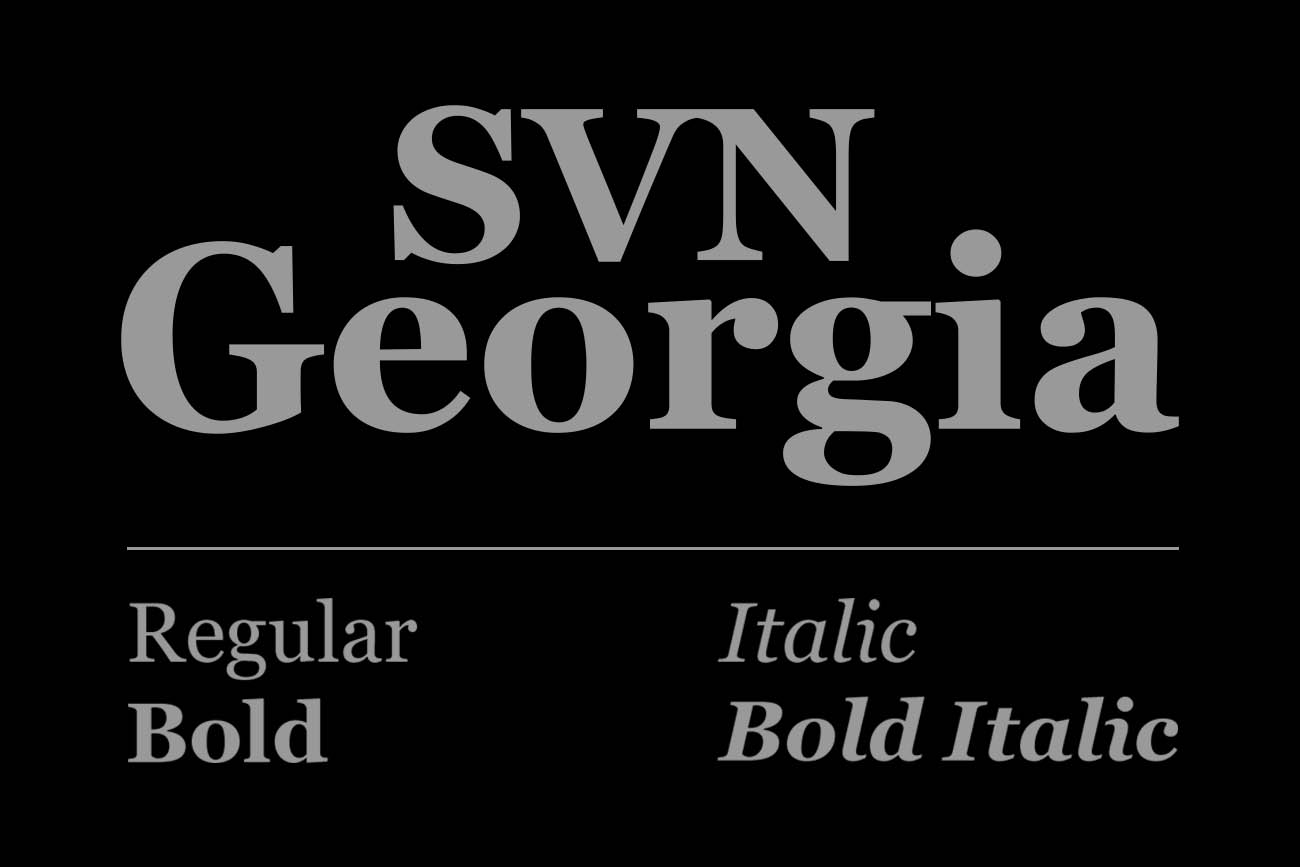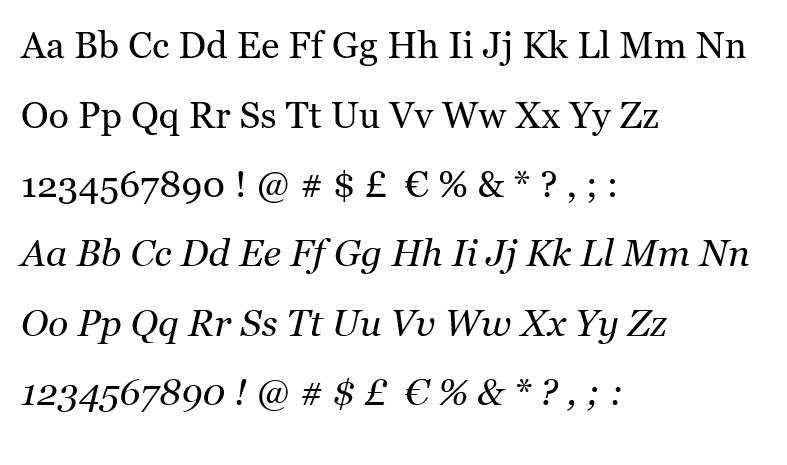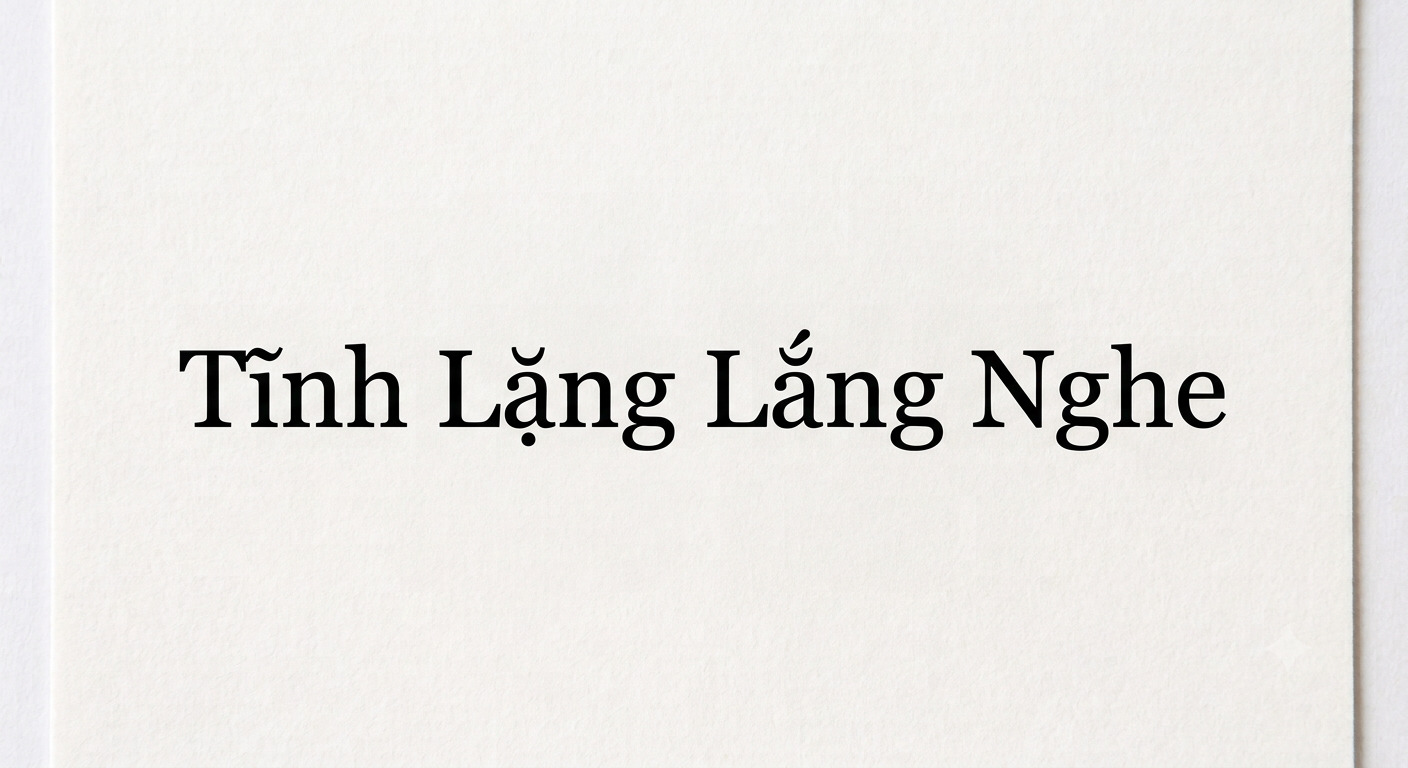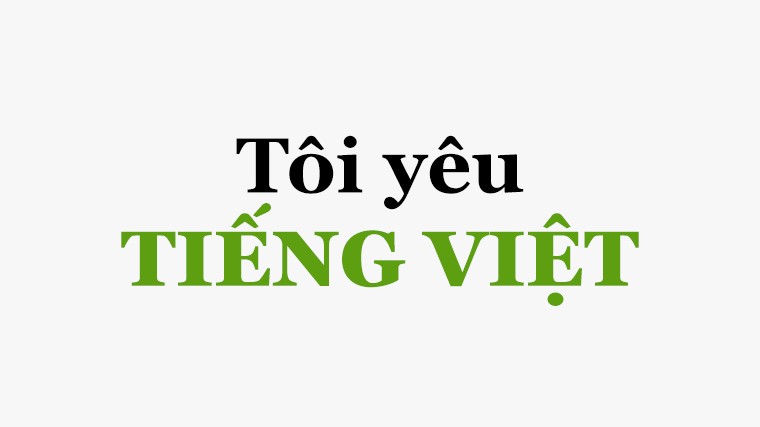
Georgia font Việt hóa là bộ phông chữ thuộc dòng Transitional Serif kinh điển được sáng tạo bởi bậc thầy Matthew Carter, thiết kế tối ưu hóa đặc thù cho việc hiển thị sắc nét trên màn hình máy tính có độ phân giải vừa phải và các tài liệu in ấn văn phòng. Với các đường chân chữ chắc chắn, bụng chữ rộng và chiều cao ký tự hào phóng, font Georgia Việt hóa là chất liệu trực quan tuyệt vời để các kiến trúc sư, kỹ sư trình bày các bản thuyết minh dự án nhà lắp ghép, hợp đồng kinh tế hay tài liệu báo cáo giám sát thi công.
Khung xương đầm ấm và độ sắc nét trên màn hình của Georgia font Việt hóa
Điểm cuốn hút của Georgia font Việt hóa nằm ở sự kết hợp giữa nét chữ truyền thống và kỹ thuật tối ưu hóa pixel hiển thị. Cấu trúc chân chữ có các đường cong chuyển tiếp dày dặn giúp con chữ bám chắc trên dòng kẻ ngang, ngăn ngừa hiện tượng lóa mắt khi đọc các văn bản dài.
Sự ổn định về mặt thị giác của dòng font này tạo nên cảm giác tin cậy, ấm áp và giàu tính tri thức. Khi kết hợp cùng các vật liệu kiến trúc cổ điển như tường gạch nung đỏ, vách gỗ sồi tự nhiên, biển đồng xước mờ hay rèm vải lanh trong các công trình nhà lắp ghép nghỉ dưỡng, Georgia tạo nên sự hòa quyện thẩm mỹ trầm mặc.
Tư vấn từ chuyên viên: Georgia được đánh giá cao về khả năng dàn trang văn bản dài (Body Text). Để bản thiết kế đạt hiệu quả thẩm mỹ tốt, bạn nên sử dụng phông chữ này cho phần nội dung mô tả chi tiết ở kích thước 10-12pt. Phần tiêu đề đề mục lớn có thể kết hợp cùng biến thể Bold hoặc một phông không chân hình học để tạo ra sự phân tầng thông tin rõ ràng và mạch lạc.
03 Ứng dụng font Georgia Việt hóa vào hồ sơ công trình
Nhờ vẻ ngoài mực thước và tính dễ đọc vượt trội, bộ phông chữ này mang lại giá trị thực tế lớn trong khâu hoàn thiện hồ sơ dự án xây dựng hiện đại:
- Thuyết minh giải pháp kiến trúc và Báo cáo hoàn công: Sử dụng font Georgia Việt hóa cho các văn bản giải trình kỹ thuật giúp tập hồ sơ trông ngăn nắp, thể hiện sự minh bạch và phong thái làm việc cẩn trọng của đơn vị thi công trước chủ đầu tư.
- Soạn thảo Hợp đồng kinh tế và Văn bản pháp lý: Những nét chân chữ vững vàng của Georgia rất ăn ý khi in ấn trên các biểu mẫu hợp đồng thi công nhà lắp ghép, tạo cảm giác đĩnh đạc và uy tín cho doanh nghiệp.
- Hệ thống biển chỉ dẫn và Bảng nội quy Homestay: Phông chữ này khi in trên các tấm gỗ sồi mộc hoặc bảng mica trong suốt sẽ giúp các khu vực chức năng trong khu nghỉ dưỡng toát lên chất nghệ thuật trầm tĩnh, giúp du khách dễ dàng tra cứu thông tin.
03 Lưu ý bố cục SVN Georgia Pro duy trì tính trang nhã
Để khai thác hiệu quả vẻ đẹp của dòng font có chân học thuật này mà không gây cảm giác nặng nề cho trang in, người thiết kế nên lưu tâm một số kinh nghiệm sau:
- Cân đối khoảng cách dòng: Do cấu trúc chữ có chiều cao x-height lớn, bạn nên thiết lập khoảng cách dòng thoáng đãng (khoảng 1.4 – 1.5 lần cỡ chữ) để các dòng văn bản không bị dính nét, giữ được nhịp điệu đọc êm ái.
- Phân cấp thông tin bằng độ đậm nét: Bạn có thể tận dụng biến thể Bold của SVN Georgia Pro cho các đề mục lớn và sử dụng biến thể Italic cho các đoạn trích dẫn phụ, giúp tài liệu có sự phân tầng thị giác mạch lạc.
- Căn lề hai bên đồng đều: Georgia hiển thị rất đẹp mắt khi được căn lề đều hai bên trong các đoạn văn dài, tạo nên các khối thông tin vuông vắn như những trang sách in ấn tiêu chuẩn.
FAQs – Thắc mắc thường gặp khi sử dụng phông chữ Georgia
1. Font Georgia có dùng được trên ứng dụng Canva không?
2. Phông chữ Georgia có gì khác so với Times New Roman?
Georgia có chiều cao x-height lớn hơn, thân chữ đầm chắc hơn và khoảng cách ký tự thông thoáng hơn Times New Roman, giúp phông chữ này hiển thị dễ đọc hơn rất nhiều trên màn hình máy tính.